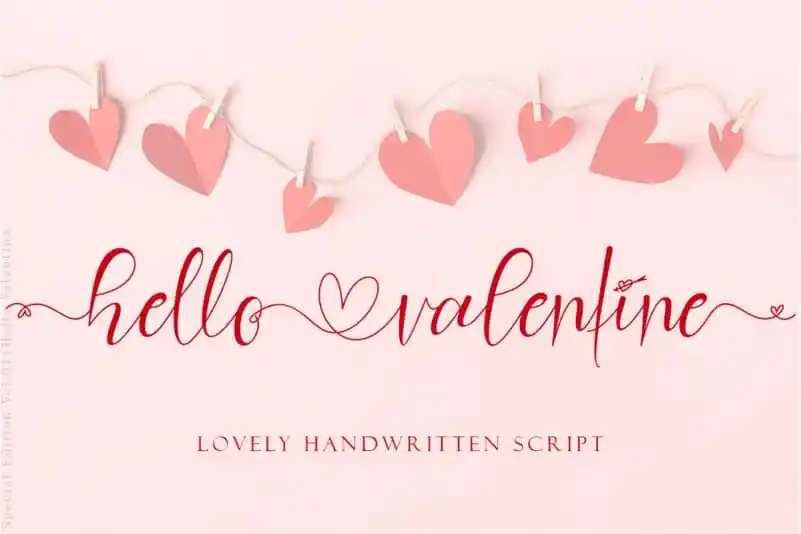
Hello Valentine Calligraphy Font – Download Grátis
Esta linda fonte se chama Hello Valentine Calligraphy Font. Ela é uma opção perfeita para quem busca uma escrita elegante e agradável, capaz de expressar com simplicidade os sentimentos mais profundos entre um par especial. O design está pensado para facilitar o uso, com guias incluídas que permitem facilmente criar uma saída gráfica perfeita. A sua beleza é inegável, tornando-a ideal não apenas para celebrar a Páscoa dos corações, mas também para registrar histórias românticas ou escrever frases de incentivo em momentos especiais como casamentos e aniversários. Ela encaixa-se perfeitamente com outros recursos visuais necessários para tornar ainda mais especial qualquer projeto. Use-a em banners, logotipos, cartões de agradecimento ou até mesmo em peças publicitárias. Seja sempre original e expressivo, é essa a essência deste belo conjunto de fontes que você encontra aqui no Hello Valentine Calligraphy Font.